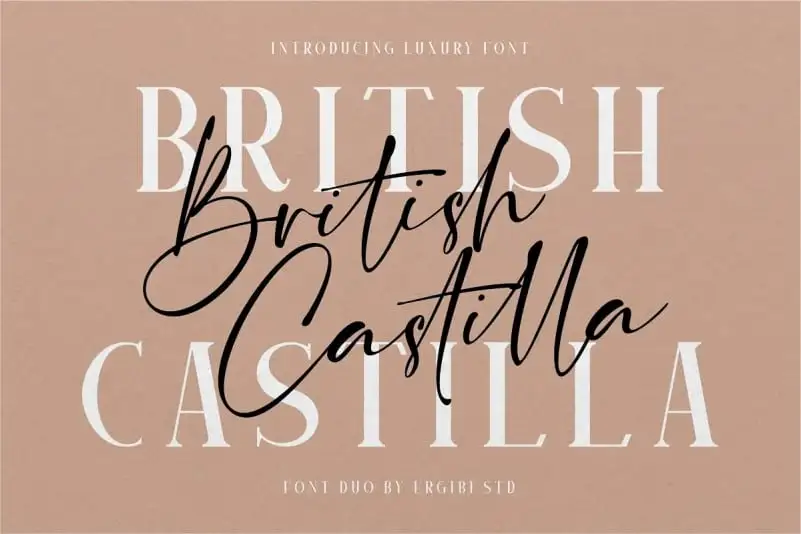
British Castilla Script Font – Download Grátis
A British Castilla Script Font é uma nova tipografia script casual e moderna, cuidadosamente concebida para trabalhar juntas de forma harmônica. Suas linhas fluidas e sutileza tornam-a perfeita para diversificar designs femininos e sofisticados. Esta fonte premium mantém seu luxo e qualidade excepcional, se adequando a uma variedade de aplicações gráficas. Ideal para headlines, logotipos, cartazes, embalagens, camisetas de tênis, lojas de café e restaurantes, cabeçalhos de revistas ou até mesmo presentes de casamento ou aniversários, seja qual for o propósito publicitário. Com sua elegância e sofisticação, a British Castilla Script Font é uma escolha conveniente para diversos ambientes criativos e comerciais.